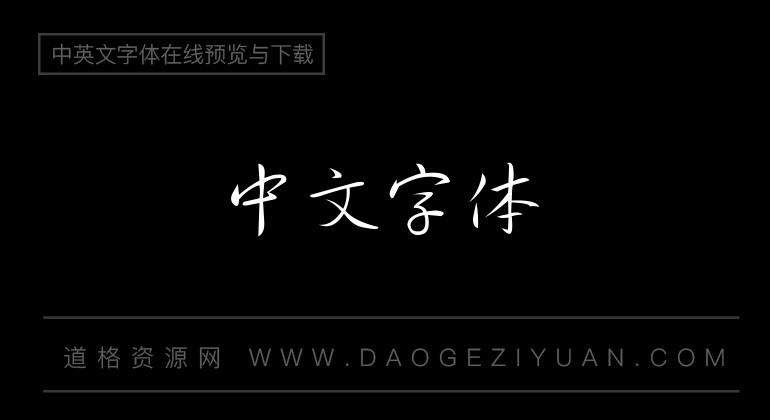
全真行书
全真行书是一种传统的中国书法字体,又称“全真书”,是中国古典书法中最古老的一种字体,最早起源于唐代。全真行书以笔画细腻、结构严谨、行书大气稳重而著称,是一种传统书法中的经典字体。全真行书的笔画细腻,结构严谨,行书大气稳重,具有较强的表现力,是中国古典书法中最古老的一种字体,也是中国书法艺术的经典之作。
全真行书是一款非常不错的手写艺术字体,具有很好的视觉感,适合于文化类的宣传设计、商业类品牌的广告和产品包装设计以及个性化文字排版等较多场景。
全真行书字符映射图